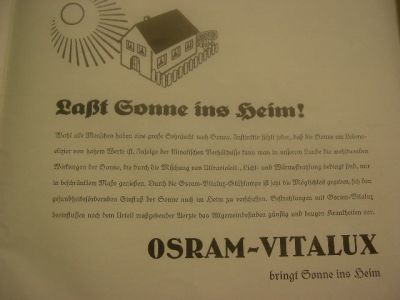
Ich sehe den Mechanismus, aber es widertrebt mir immens, den unwidersprochen zu lassen. Obwohl doch gerad ich.. der mit dem "leicht absonderlichen Bleisetzerei-Namen".. - man weiß es ja nicht, oder doch? "Ob der wohl vom Mars stammt?".
Ne,nee.. laßt uns das Thema ruhig beim Namen nennen.
Dann brauchen wir in Bezug auf "Nationalsozialismus und Schrift/Typographie" auch nicht nebulöse Worthülsen nutzen. Eins greift ins andere.
finde ich nicht unbedingt. schriftnamen und schriften selbst sind doch immer von ihrer zeit geprägt, und in der zwischenkriegszeit, vorallem natürlich ab 1932, waren "grossdeutsche" und nationalistische tendenzen und vorlieben natürlich verbreitet.
den gestaltern, die ja oft erfüllungsgehilfen von marktwünschen sind, dabei eine nationalistische oder gar nazistische haltung zu unterstellen, finde ich dann doch ein bisschen übertrieben. und durch form und namensgebung dann auch noch gleich den schriften eine politische haltung zu unterstellen.. naja. (vielleicht mal abgesehen von der "Großdeutsch")
von der helvetica behauptet ja auch niemand, dass sie eine nationalistische schrift sei. die wurde aus marketinggründen von neue haas grotesk in helvetica umbenannt. genau das gleiche würde ich bei den von dir genannten schriften auch erwarten.
Wie bereits erwähnt: Die Schlacht um Tannenberg fand Ende August 1914 statt. Es gelang dort, einen russischen Einmarsch nach Ostpreußen ins Reich zu verhindern. Diese Schlacht war maßgeblich.
Nichts am Namen Tannenberg hat nationalsozialistischen Charakter, wirklich nichts.
Ich lese gerade das aktuelle Geo Epoche, Thema: Französische Revolution. Wenn heute ein französischer Politiker an den Sturm auf die Bastille erinnert und die Glorie Frankreichs hervorhebt, unterstellt ihm niemand Nationalismus - und selbst wenn: Niemanden würde es stören.
Wenn in Deutschland 1934 eine Schrift entworfen wird, die "Tannenberg" genannt wird, über deren relative Schönheit man streiten kann und die durch ihre Gestaltung eben aus damaliger Sicht das Monumentale des nationalen "Heiligtums" Tannenberg nachempfinden sollte, einer Schlacht, die 20 Jahre zuvor stattgefunden hat, dann echauvieren sich 72 Jahre danach bei uns die Typographen.
Es ist erstaunlich.
Fragen
Gibt es eigentlich ausländische Frakturschriften aus dem gleichen Zeitfenster, die formal ähnlich gestaltet? Habt ihr Beispiele?
Ist die Entwicklung zu solcherlei vereinfachten Formen, keine aus der Sicht des damaligen Schriftgestalters heraus, logische Entwicklung *, die zu solchen oder ähnlichen Gestaltungsergebnissen führt/führen kann?
Provokativ gefragt:
Sind vereinfachte Formen, die den Formenkontrast steigern,
Fette Schnitte die Kontrast steigern,
politisch, nationalsozialitisch oder sind diese nicht eher plakativ, werberisch, Aufmerksamkeit erheischend und somit auch tauglich für Progagandazwecke?
* Das durch die breite Akzeptanz der Groteskschriften in Deutschland, wie International, als Auszeichungsschriften in den Bereichen Werbung etc. die Schriftgestalter auch im Bereich Fraktur beeinflusst worden sind.
Ich bin in meiner Bewertung auch nicht ganz sicher. Mir scheint es ein Ausnahmefall zu sein mit diesen vereinfachten Gotischen. Die DDR z.B. hatte keine Schriften, die wir heute sofort mit sozialistischer oder kommunistischer Propaganda verbinden. Es gab ein bißchen "Reporter", die Pinselschreibschrift, und dann diverse Serifenlose auf den Bannern und Plakaten. Die Gestalter, die diese Schriften namens National und Tannenberg usw. entworfen haben, befanden sich sicherlich auch in dem Sog der Zeit, man glaubte 1934 an Aufbruch und Fortschritt, man konnte rasch Karriere machen, Bürokratie wurde abgebaut usw., die Schriften von Götz Aly geben uns ja in jüngerer Zeit neue Sichtweisen auf die modernen Züge des Dritten Reiches und wieviele Menschen davon profitierten. Also mit Gut und Böse läßt sich das Phänomen nicht greifen. Aber sind diese genannten Schriften nicht heute und für uns eindeutig eben dieser Zeit, dieser Stimmung, dieser Politik und diesem Land zuzuordnen? Wenn das so ist (ich bin da noch nicht sicher), dann sind es eben doch politisierte Schriften und man transportiert im Gebrauch dieser Schriften die Ideologie weiter. Ein Beispiel: Wenn jemand in meiner Druckerei Einladungen zu einem "Gartenfest" aus "Fette Deutschland" bestellt (die ich nicht habe), würde ich mich zumindest wundern, wenn nicht sogar nachschauen, ob draußen noch Jungs mit Baseballschlägern und bissigem Hund im Auto sitzen.
Genau solche ‹internationalen› Tests hat Walter Plata mit Frakturschriften gemacht. Leider muss man ihn, den beinahe schon fanatischen Fraktur-Liebhaber, jedoch etwas der Voreingenommenheit verdächtigen – und zudem hat er das ganze Arrangement reichlich konfus beschrieben.